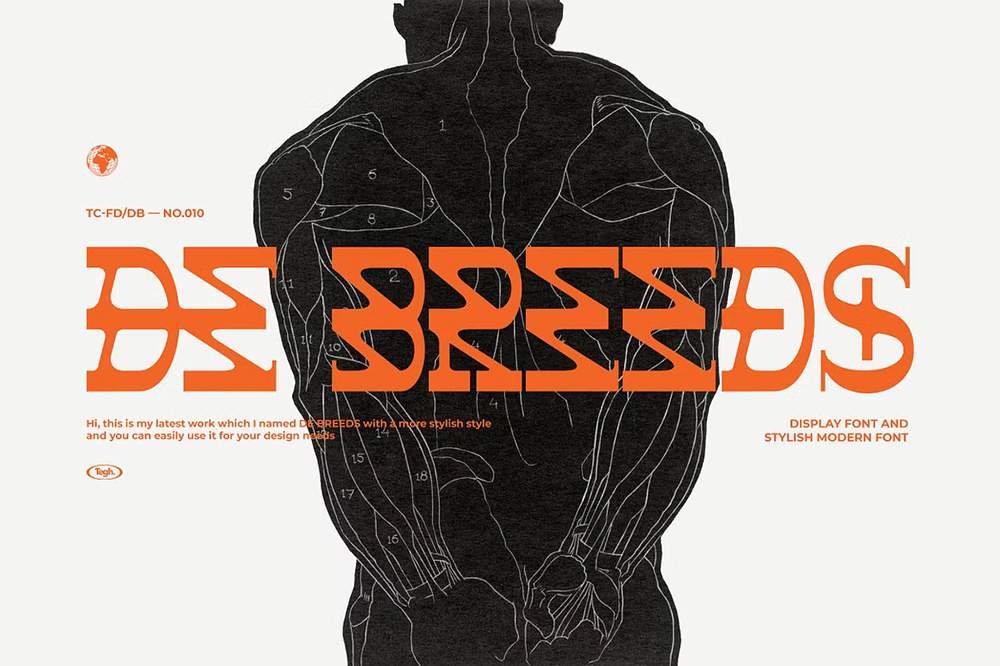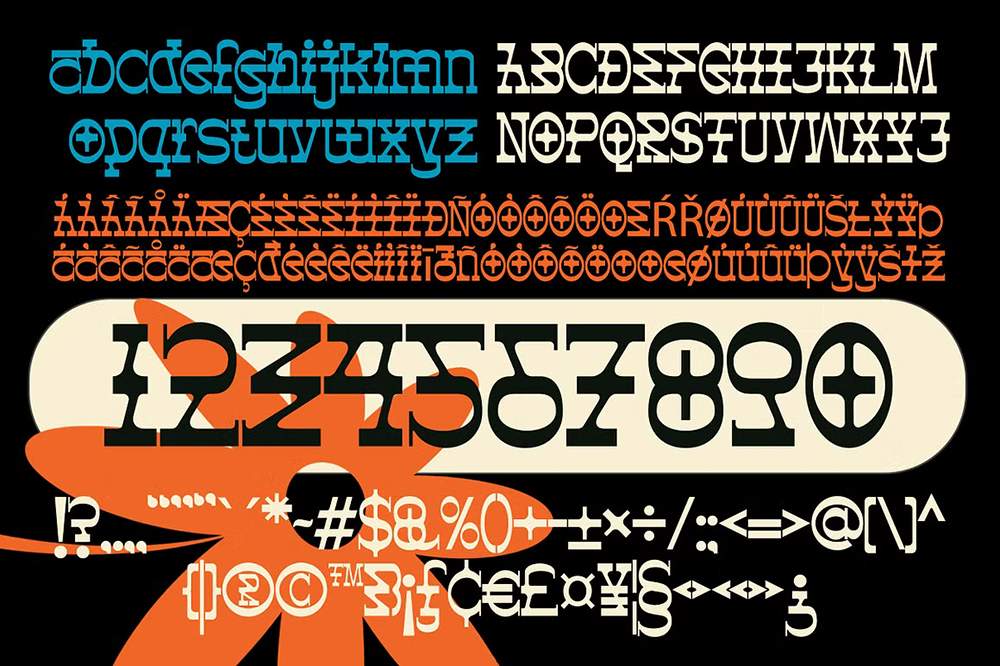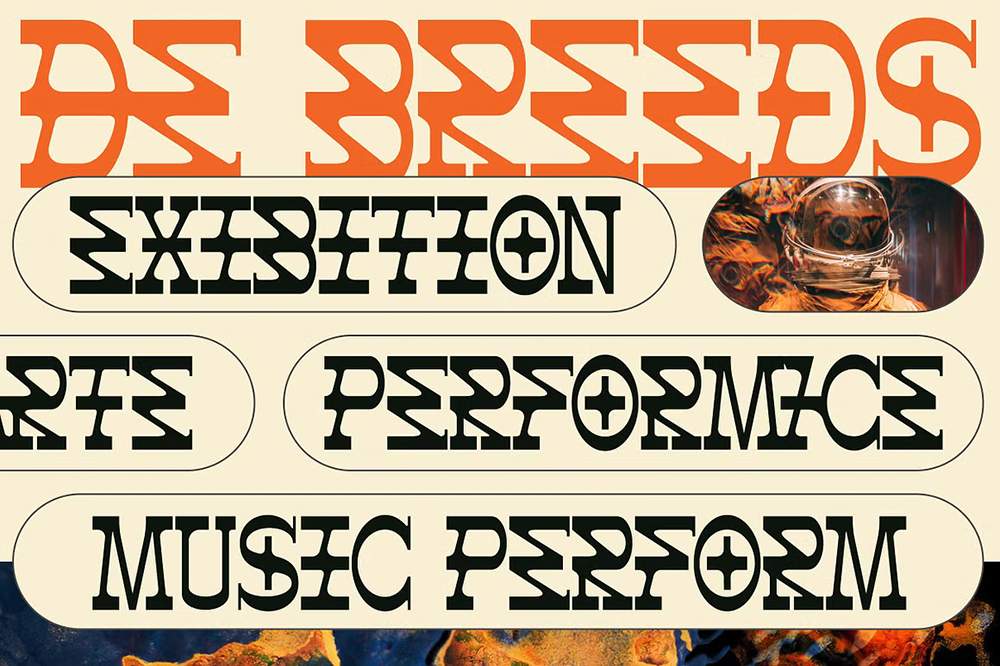
دانلود فونت انگلیسی DE BREEDS Font
فونت پرمیوم و انگلیسی DE BREEDS Font يک فونت شيک و منحصر به فرد که میتوانيد به عنوان يک افزودني بصری به طرحهای خود جمعآوری کنيد. اين بار اين فونت ايجاد طرحهايی مانند پوستر، استيکر و موارد ديگر را برای شما آسانتر میکند.
مزایای استفاده از فونت لاتین DE BREEDS چیست؟